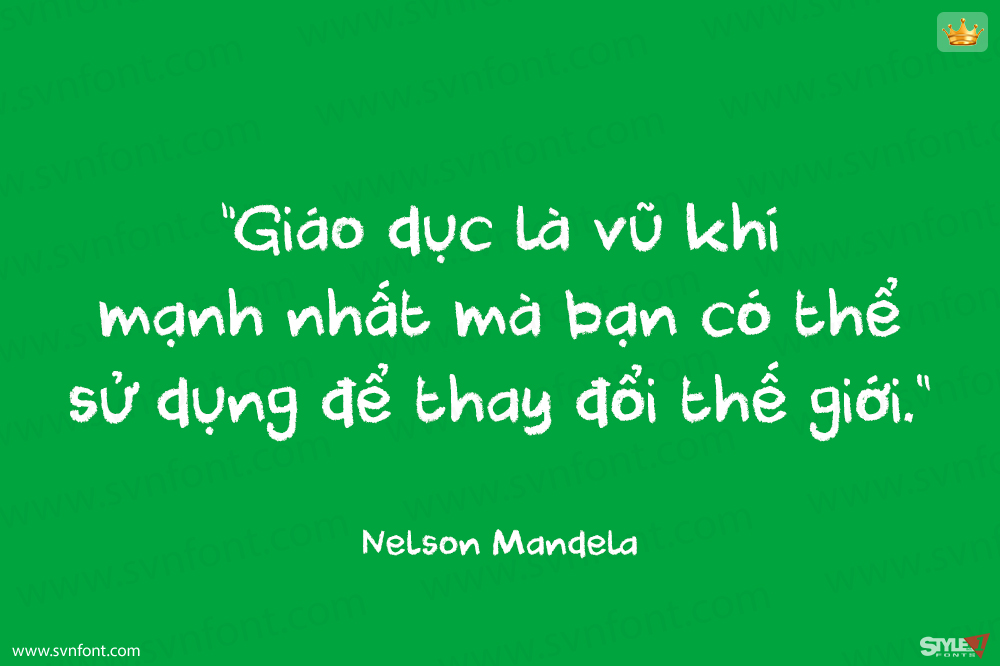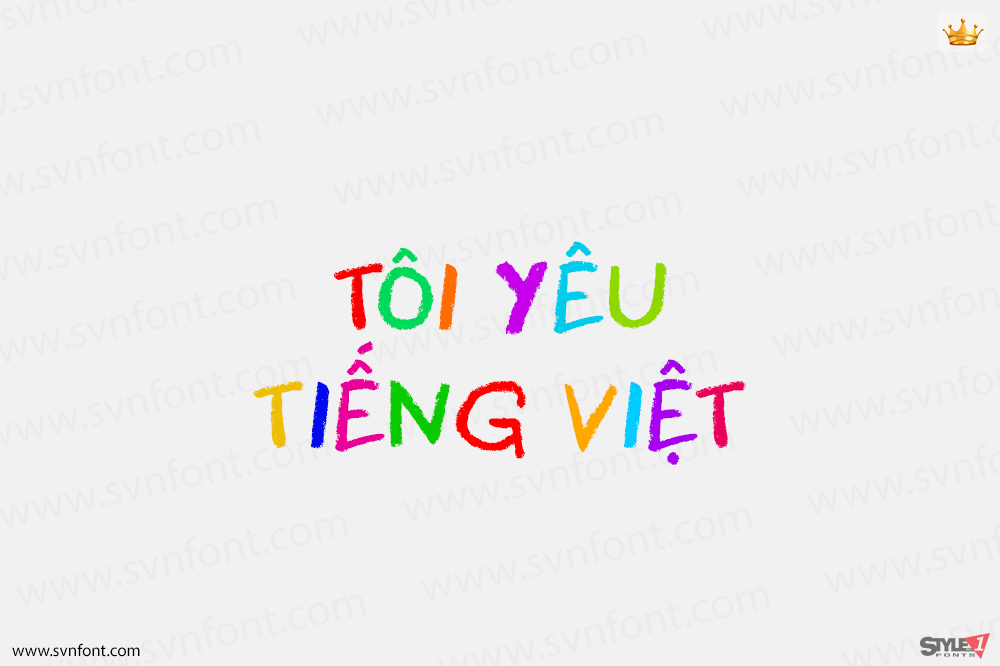
Cool Crayon là một kiểu chữ đẹp mà tôi đã tạo ra bằng cây bút chì màu đen Crayola từ hộp bút chì màu của con trai 3 tuổi. Nó đã bị gãy (vì thằng bé có xu hướng ném chúng lung tung), nhưng tôi đã cố gắng vẽ các glyph lên một tờ giấy. Cool Crayon tương tự như Crayon Crumble, nhưng tròn trịa và dày hơn. Cool Crayon đi kèm với hỗ trợ ngôn ngữ mở rộng.
Nhà thiết kế: David Kerkhoff
Nhà phát hành: Hanoded